K-POPアイドル「TWICE」「EXO」「Stray Kids」「LE SSERAFIM」「ITZY」「NewJeans」「aespa」などのグループを中心にK-POPアイドルは日本でも人気があります。
今回は、そんなK-POPアイドルの推し活にぴったりな韓国語(ハングル)のフリーフォントをご紹介します。
K-POPアイドルを応援する際、オリジナルの画像や動画の制作、コンサートで持参するグッズの制作など、多様な場面で活躍するフォントがたくさん紹介しています。
「K-POP」アイドル推し活に使える韓国語フリーフォント
以下のサンプル画像は、本記事で紹介していている「K-POP」アイドル推し活で使える韓国フリーフォントの1部ですが、韓国フォントも多種多様で可愛いフォントが多くて、見ているだけでも楽しいですね。ぜひ、自分にぴったりなフォントを見つけてみてくてださいね。
평창평화체【デザイン系】
文字の中にキランと星のモチーフが埋め込まれているのが、とても可愛らしいフォントです。韓国国内のYoutube動画やサムネイルで人気のあるフォントです。
韓国でも流行っているY2Kデザインにとっても合っているデザインなので、K-POPアイドルの推し活グッズ制作に向いているフォントです。
Bagel Fat One【デザイン系】
こちらのフォントも韓国国内のYoutube動画のテロップやサムネイルで人気のあるフォントのようです。
日本語のフォントではあまり見かけないタイプのちょっと変わったフォルムが可愛らしいフォントなので、インパクトがあるので、目立つこと間違いないフォントです!
고령딸기체【デザイン系】
光沢のようなデザイン模様がついているのが特徴的なデザイン。太めで可愛い雰囲気の韓国語フォントを探してるならこちらがおすすめです。
창원단감아삭체【丸ゴシック系】
視認性ギリギリまで太めにしているのが、インパクトもあり愛らしさもあるフォントです。ライブやコンサートに持っていくK-POPアイドルの推し活グッズ制作するなら、おすすめです!
Gasoek One【ゴシック系】
上記の「창원단감아삭체」フォントより、丸みを少し抑えた印象の極太ゴシックフォントです。インパクトがありドドンと目立つ文字なので、同様にコンサートに持っていく推し活グッズ制作するなら、こちらのフォントがおすすめです!
CAFE24 PRO UP【デザイン系】
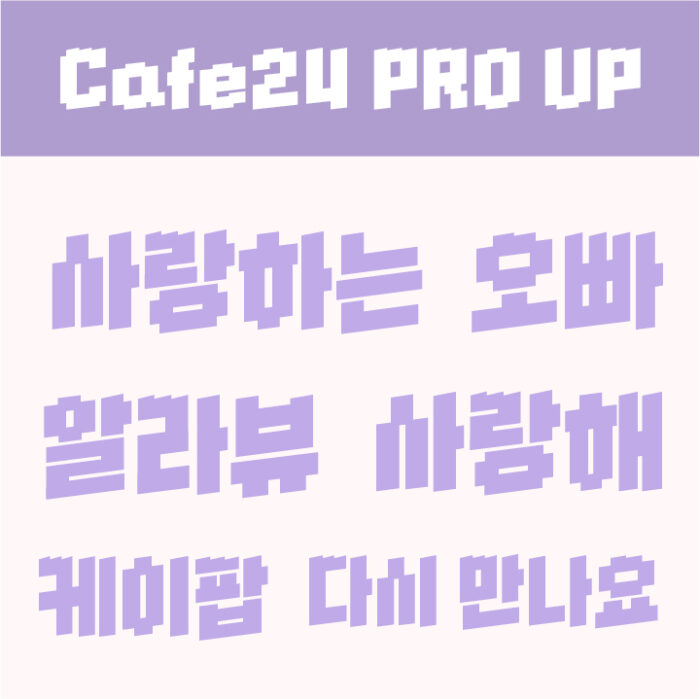
CAFE24 PRO UPフォントは、上辺がデコボコとしたユニークデザインのフォントです。ピクセルフォントのようなゲームっぽい雰囲気を作りたい場合にぴったりです。
Single Day【手書き文字系】
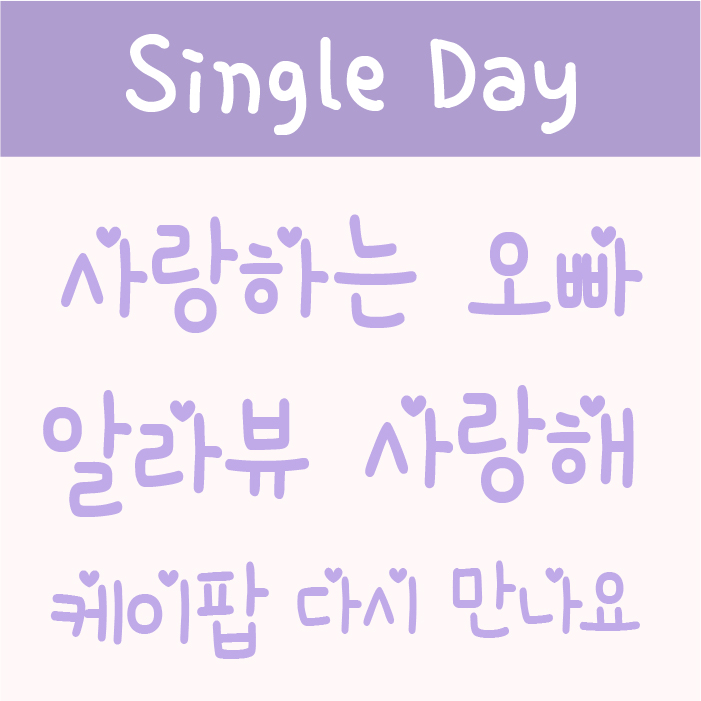
文字の中にハートのイラストが隠れている可愛いフォントです。手作りのアクスタやキーホルダーなど作るならおすすめです。
個人的に一番かわいい韓国語の手書きフォントだと思っています!
카페24 숑숑【手書き文字系】
かわいい手書き文字系の韓国語フォントを探している方にはこちらがおすすめです。카페24(cafe24時)シリーズはとても可愛いフォントばかりなので、おすすめの韓国語フォントメーカーです。
카페24 슈퍼매직【手書き文字系】
こちらも同様に「카페24(cafe24時)」からおすすめです。サインペンやマジックのような太めのペンで書いた手書き韓国語フォントです。
땅스부대찌개【丸ゴシック系】
日本語で言う丸ゴシックやフォーク体のような丸っこいフォルムが可愛らしいです。K-POPの推し活グッズを、しっかりした文字で表現するにはおすすめです。
태백체【ゴシック系】
日本語でいう「ゴシック体」のベーシックなフォントです。汎用的に幅広い場面で使えるフォントなので、とっても使いやすいかと思います。
파셜산스【デザイン系】
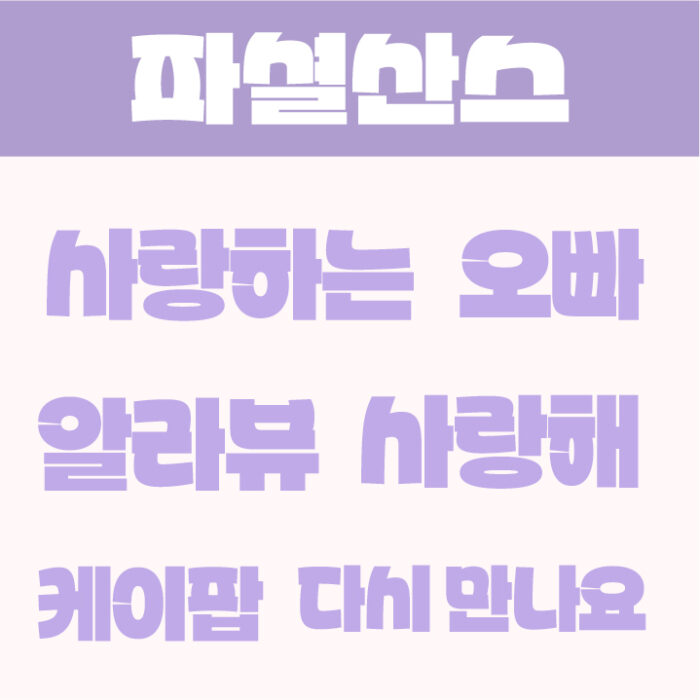
日本語でいう「ポップ体」のような丸みが可愛らしいハングルフォントです。可愛さと読みやすさを兼ね合わせているデザインフォントです。
국민연금체【丸ゴシック系】
こちらもベーシックな丸ゴシック系を探しているなら「국민연금체」もおすすめです。曲線と角丸の具合が良いバランス感で使いやすい韓国語の丸ゴシックです。